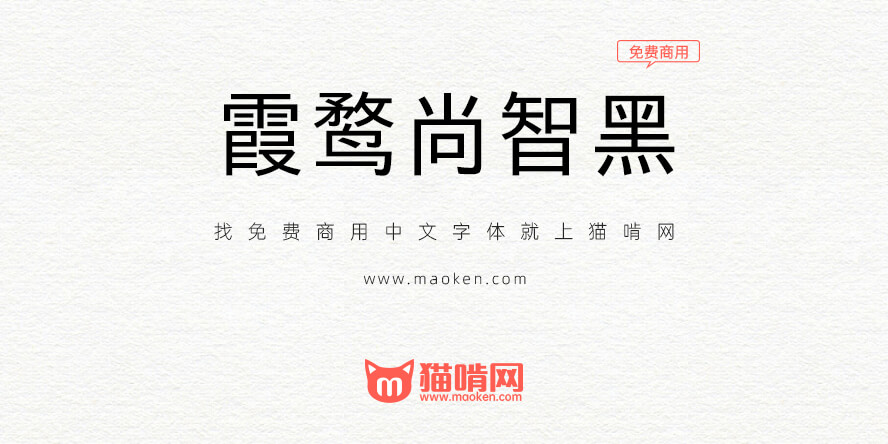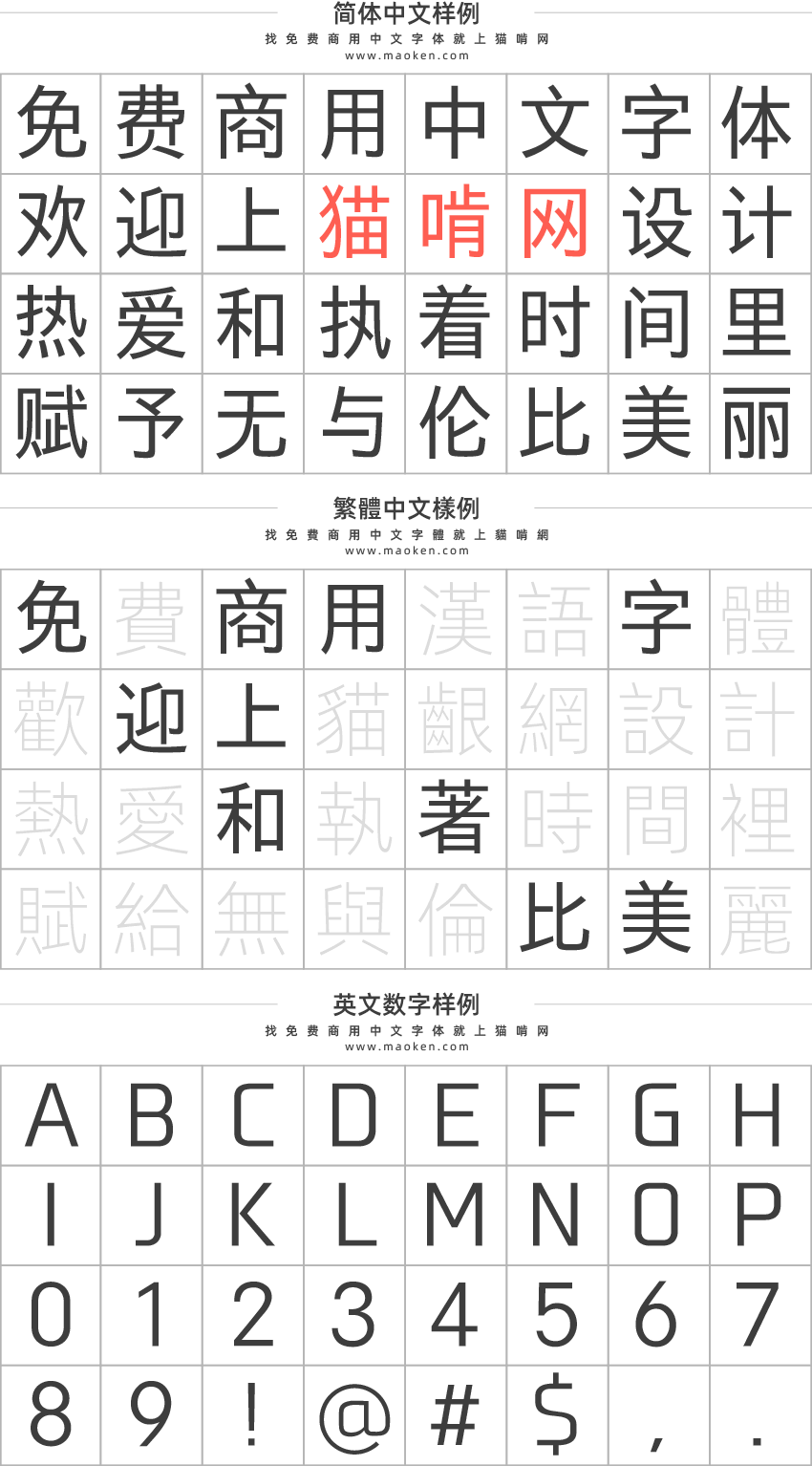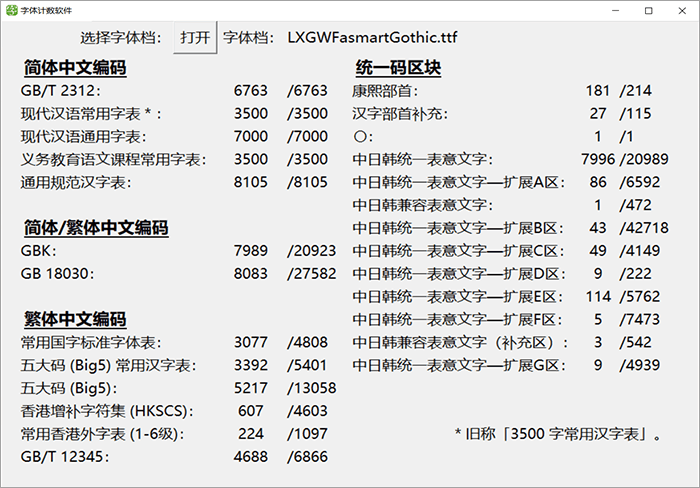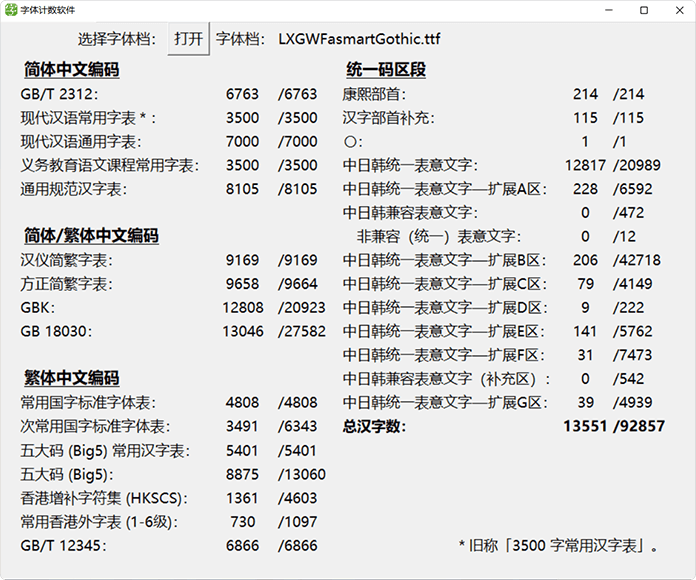
基于「03スマートフォントUI」以及「霞鹜新晰黑」「霞鹜晰黑 CL/MN」衍生的中文黑体字型。
将字面横向压缩 94%,全新英数与假名,更具稳重时尚感。
- 本字体项目现已单独设立 repo,不再随附于《霞鹜新晰黑》,并且不再与新晰黑同步新增或调整字符。
不同字形版本及收字情况
- 霞鹜尚智黑: 采用中国大陆规范字形(GB 字形)。收录的汉字部分与 霞鹜新晰黑 v1.124 看齐。
- 霞鹜尚智黑 CL: 参考早期铅字印刷字形常见写法,回归旧式印刷字形,合并一部分「源规格分离」原则下分化的异码字。收录的汉字部分与 霞鹜晰黑 CL v0.321 看齐。
- 霞鹜尚智黑 MN: 采用兼顾当代惯用部件写法的折中印刷字形(非楷化字形),严格遵循「源规格分离」原则。收录的汉字部分与 霞鹜晰黑 MN v0.321 看齐。
- 尚智黑所收的符号相比于新晰黑会有所欠缺。
数字很棒和黑体很配,就是字母有些柔